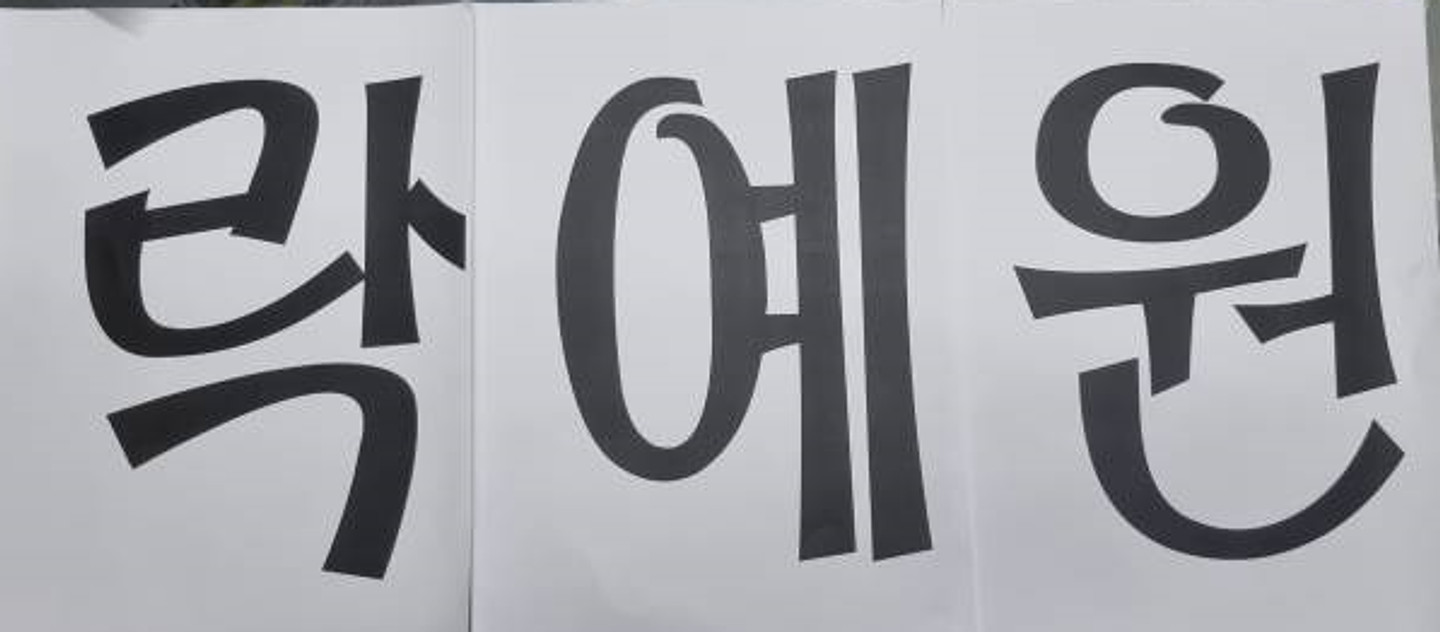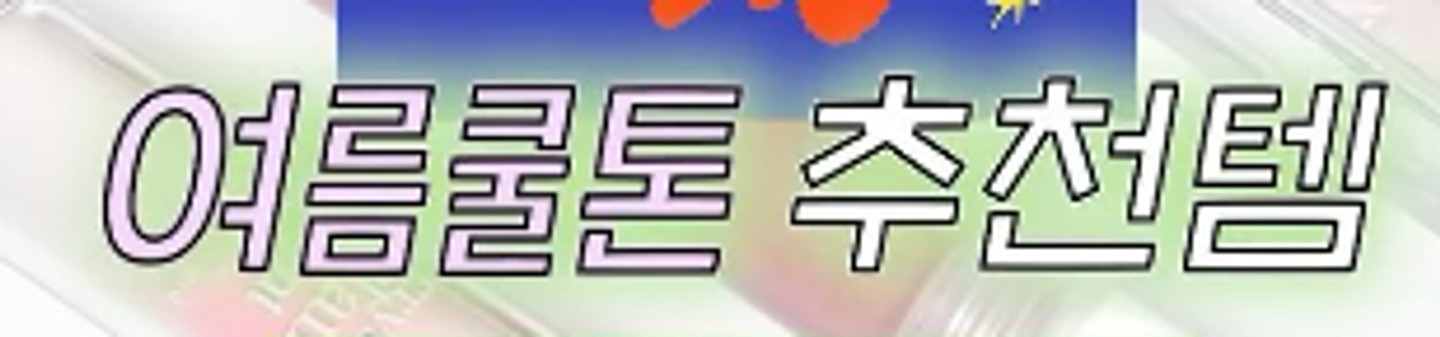
혹시 the에 쓰인 폰트랑 Nouveau Table에 쓰인 폰트가 뭘까요?
이 폰트에 대해서 궁금합니다. 2024년 강릉문화유산야행 홈페이지에 사용되었습니다. http://www.gncn.or.kr/web2021/main.php
유튜브에서 옛날 음악방송 보다가 자막에 나온 글씨체보고 궁금해서 질문합니다. 무슨 글씨체일까요?
이 폰트 뭔가요 선생님들
이거 폰트 알려주세요
이 글씨체 아시는 분 계신가요??
이 폰트 아시는 분 계실까요! 이 폰트 아니더라도 저 폰트처럼 겉부분이 불규칙한 느낌의..폰트 추천 부탁드립니다..!
이 세렌디피티 폰트가 뭔지 알고 싶습니당... 도와주세요
유월음악회 폰트 궁금합니다
무슨 폰트인지 알고 싶습니당 i 위에 점이 반짝이 모양이고 각 알파벳들 높낮이가 다른 게 특징인 것 같아요
무슨 폰트인지 알고 싶습니당
무슨 폰트인지 알 수 있을까용
알려주시면 감사하겠습니다…
사용된 폰트가 뭔가용?
위 이미지에 사용된 서체 알려주세요
이 폰트 무엇인가요??
보건복지부 내홈페이지에서 인쇄한 파일의 글씨체입니다.
이 영문 폰트 뭘까요?! 에밀 루더 - 타이포그래피 책에서 '움직임' 챕터에 예시로 나오는 편집 디자인입니다. 지나 가려다가 폰트가 너무 예뻐서 궁금해졌어요! 혹시 아시는 분들 있을까요?
뒤집어지는 영화관 콜라보 근황 폰트 알 수 있을까요??
이 폰트 아시는 분 부탁드려요! 지마켓산스인 줄 알았는데 아니더라고요ㅠㅠ (묘하게 굵기가 다르고 숫자 3 모양이 달랐음ㅠ)
여기 나오는 폰트가 뭔지 아시나요?
요거 혹시 무슨 폰트인지 알 수 있을까요?
뚱뚱한 일본어체 이름이뭔가요 ..?
이게 무슨 폰트에여?
무슨 폰트인지 궁금해요~~ 도와주세요~~ 감사합니다.^^
사진에 폰트가 무슨 폰트인가요?
이 폰트는 무슨 폰트인가요?
이거 무슨 폰트 일까요 ㅠㅠ?
이 폰트 제발 어떤걸까요ㅠ
많이 본 폰트인데 이름을 모르겠네요 ㅠ 아시는 분 계신가요...
이 폰트 아시는분 있나요..? 아니면 비슷한 폰트라도 알려주세요ㅜㅠㅜㅠ
이거 폰트 다 알려주실 수 있나여..?
금영 cl입니다
폰트 이름 아시는 분~~~ 알려 주세요.
이거 많이 본 폰트인데 막상 찾으려니까 모르겠네요.....
사용된 폰트 어떤 건지 알려 주시면 감사하겠습니다 ㅠㅠ!!
폰트 질문이요!
오늘의집의 <월간집들이> 무슨 폰트인지 궁금합니다.
폰트 문의드립니다
카톡창 폰트 뭘까요?
'영남 맛 단무지' 폰트 아시는분 ㅠ
폰트가 궁금해요 ^ ^
글씨체 찾아주세요 ~~!ㅜ
제일 비슷한 폰트 어떤건지 아시는 분ㅜ
황비웅비 글씨 알려줘
이거 해운대여행1순위코스 폰트 어떤건지 아실까요?
이 영어 글씨체 어떤 폰트일까요?ㅠ
무슨 폰트인지 아시는 분 계실까요?
화로우 폰트 어떤건지 아시나요 ㅠㅠ? 급합니다
영문폰트같은데 알려주세요!!! 감사합니다 :)
안녕하세요, 해당 서체가 어떤 것일지 궁금합니다. 알려주시면 정말정말 감사드리겠습니다 🥹
이 폰트 무엇인가요?ㅠㅠ 산돌구름 돌려도 안나와서 여쭤봅니다..
이거 무슨 폰트인지 아시는 분 ㅠ 기존 폰트 수정해서 사용한거라면 기존 폰트 좀 알려주세요..
ㅜㅜ 폰트 정보가 궁금해요
고수님들! 무슨 폰트일까요??
"에"자입니다. 폰트가 어떤 폰트일까요?